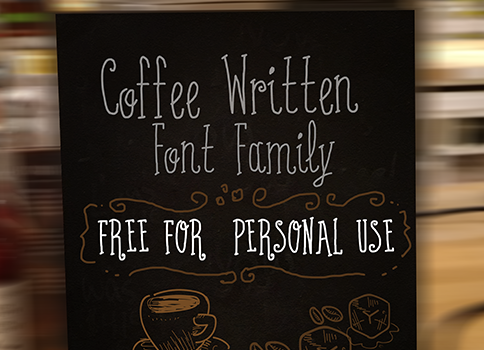
Coffee Written Typeface – Download Grátis
A fonte Coffee Written é perfeita para quem deseja adicionar nuances e sutilezas a seus designs, especialmente quando trabalha com textos sobre café ou tem uma paixão pela bebida. Desenvolvida pelo designer Galdino Otten, esta família de tipos foi projetada para comunicar os sentimentos que você experimenta logo cedo em um bom café colombiano. O nome é uma referência à própria fonte; suas linhas e detalhes carregam o sabor, textura e paixão do melhor café. Coffee Written traz sementes de personalidade a cada design, seja para um projeto pessoal ou compartilhado com amigos e pessoas especiais. Essa fonte oferece uma experiência única em que cada letra contém nuances suaves e profundas, garantindo que seu design sempre tenha uma nota especial. As linhas fluidas e os detalhes delicados dão ao Coffee Written um toque único, adaptável tanto a projetos pessoais quanto colaborativos, permitindo às pessoas expressar suas ideias de maneiras distintas e personalizadas. Este é mais do que apenas uma fonte; ele é uma extensão da sua criatividade, um companheiro sempre presente na hora de criar qualquer design.